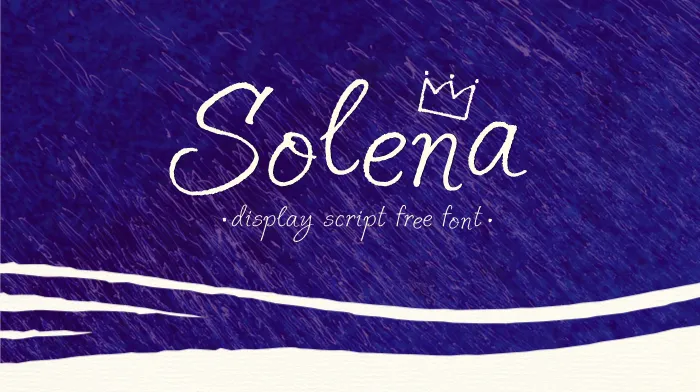
Bem-vindo ao mundo da Solena Script Font! Esse é um tipo de letra que parece ter sido feito à mão, criando uma sensação quase mágica nas suas criações digitais. Para os amantes do design gráfico e das artes visuais em geral, este fonte é perfeito. Cada caractere na Solena Script Font carrega consigo um sentimento de originalidade e frescura. O designer Hamilton criou essa fonte com uma pitada de sofisticação e muita personalização. Ela se destaca entre outras cenas digitais por sua textura única, permitindo que você personalize suas criações de forma única, desde pequenos detalhes até o grande projeto final. Com a Solena Script Font na sua coleção, poderá transformar qualquer documento ou design em algo realmente especial e único. Não é apenas um complemento para suas criações digitais, mas também uma ferramenta que permite que você entre em contato com seu público de maneiras diferentes e criativas. Seja no âmbito pessoal ou empresarial, a Solena Script Font oferece uma variedade de possibilidades. Então, se estiver procurando por algo que vai dar vida à sua ideia, procure aqui uma fonte que é tanto original quanto versátil. Descubra como transformar suas ideias em realidade com esta incrível opção!